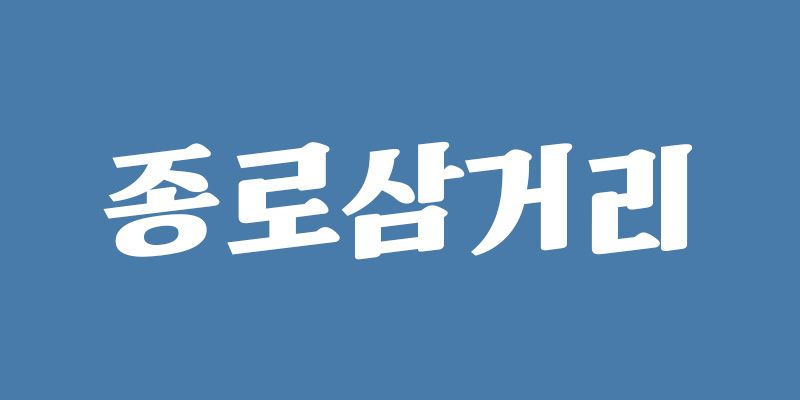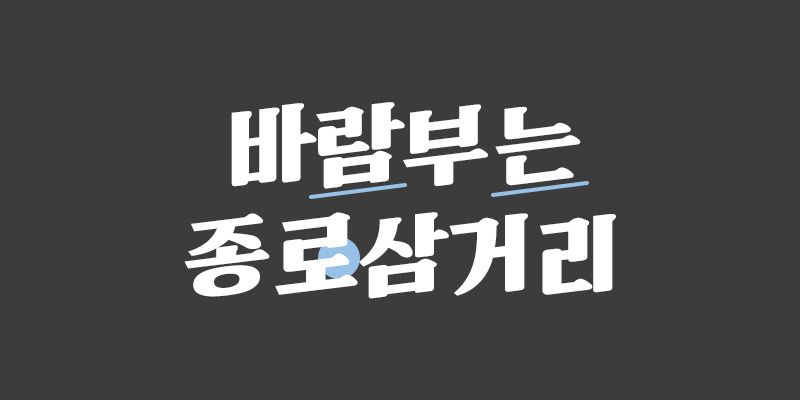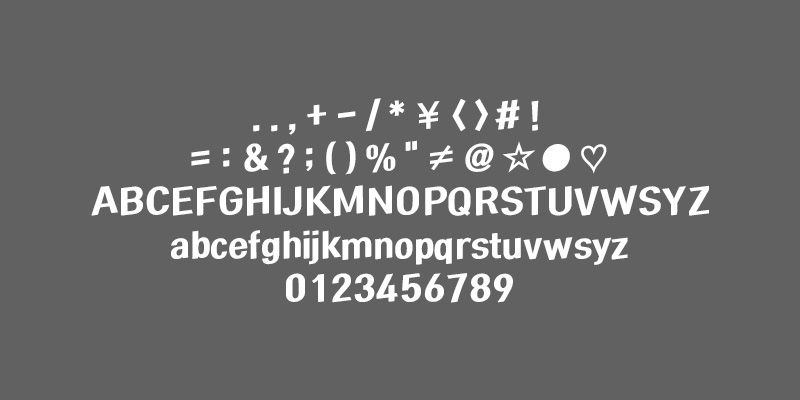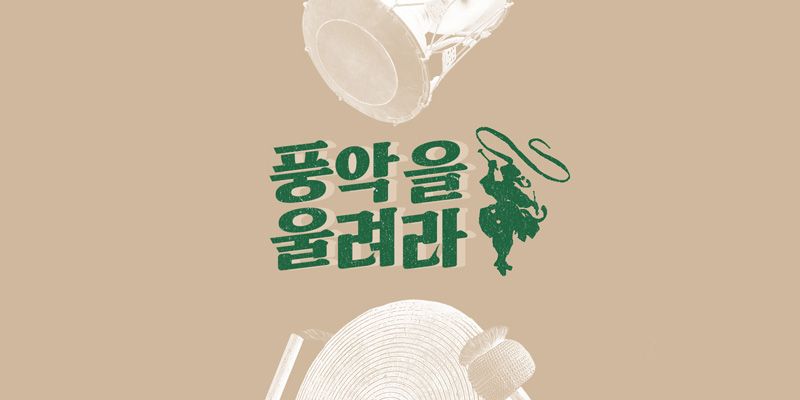
RixJongno est une police avec empattement à l’aspect doux et convivial. Elle est idéale pour accentuer les expressions et renforcer les idées, avec ses courbes vigoureuses et sa structure carrée pleine. L’écriture verticale prend un aspect esthétiquement plaisant grâce à son axe vertical incliné.